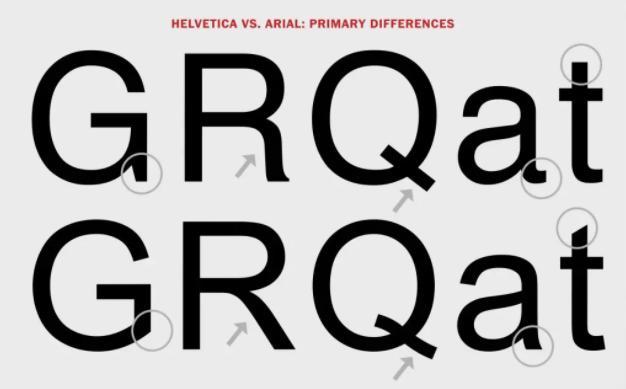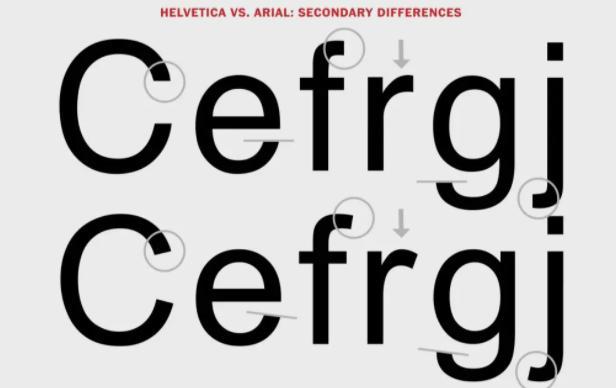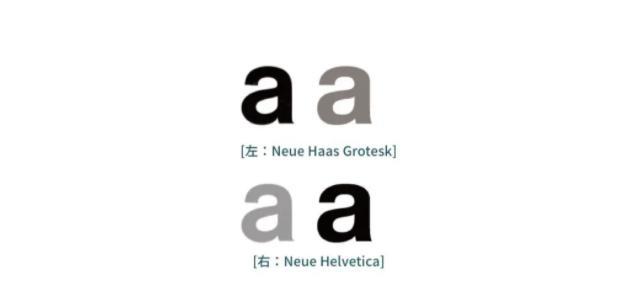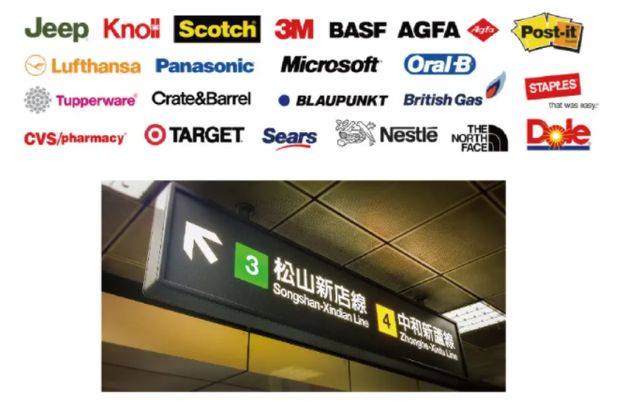
挽救铸字厂的事业的新字体
1950 年代,瑞士哈斯(Haas)铸字厂的老板爱德华奥夫曼(Eduard Hoffmann. 1892–1980)发现自己公司的无衬线体Franzsische Grotesk 和Normal-Grotesk 在市场上的占有率越来越低;相反地,对手伯特霍尔德(Berthold)铸字厂的Akzidenz-Grotesk 字体,却因搭上了国际主义设计风格(International Typographic Style)的顺风车,在当时显得更「现代」,也因此成为那个年代最受设计界欢迎的非衬线体。
但危机或许就是转机。哈斯铸字厂意识到他们需要设计一种新的字体──这个字体除了要更现代、简明、清晰之外,奥夫曼和字体设计师马克斯米丁格(Max Miedinger, 1910–1980)更想设计出一种真正「中性(neutral)」的字体,一种不带有其他涵义,让读者不会被字体本身的装饰分心、能够单纯传达文义的字体。
新字体的设计在 1956 年秋天如火如荼展开,米丁格在图纸上来回打稿。他先是统一了过去c, s, f, j 等字母笔画末端风格不一致的问题,空出了较大的x-height,让读者即使站在远处,也能清楚辨识;另外,他也缩小了字母与字母之间的间距,让整体文本看起来更为紧凑鲜明。
在新字體發表的前夕,米丁格將它命名為「Neue Haas Grotesk」,德文的語意為「新的/Haas 廠生產的/非襯線體」。1957 年,Neue Haas Grotesk 甫正式發表就獲得極大迴響,許多設計師好像終於找到了他們心目中的「理想字體」了。
不過對哈斯鑄字廠來說,這樣還遠遠不夠,要和其他鑄字廠的字體競爭,還需要藉由更廣泛、通用的媒介來宣傳 Neue Haas Grotesk。
以拉丁文命名
为了拓展新字体的使用率,1959 年奥夫曼和德国史丹普印刷厂 (D. Stempel AG )达成合作协议,让 Neue Haas Grotesk 成为该公司 Linotype 自动排字机的预设字体。
Linotype 在这里不是指 Linotype 公司,而是一种机器,是 Line-of-type 的缩写,意即「一行活字」。过去没有 Linotype 自动排字机时,排字员需要手动取下一个一个铅字,然后费时逐字排版。
报纸或杂志这类具时效性的印刷物,并不像书本有时间慢慢排,毕竟若今天的新闻要花好几天才能排完送印,届时岂不就成为了「旧闻」?
但在1884 年奥特玛·默根瑟勒(Ottmar Mergenthaler,1854–1899)发明Linotype 自动排字机后,将人工取字的过程大幅自动化,加速了由排版到送印出版间所需的时间,印刷厂可以在雇用和以往同样人数的排字员下,完成更多页面,造就了整个印刷产业的革新。
直到 1980 年代照相排版(phototypesetting)技术成熟前,世界上多数的报纸、杂志和海报都是透过这种机器进行排版。
达成协议固然是好事,不过史丹普的销售经理却觉得Neue Haas Grotesk 这个名字太饶口,建议重新命名为Helvetia(拉丁语瑞士(名词)之意),但因为这个名字已经被当时的保险公司和缝纫机公司采用了,所以奥夫曼建议使用另一个名字:Helvetica,这是拉丁文「瑞士的(形容词)」的意思。
顺带一提,身为一个拥有四种官方语言(德语、法语、义大利语、罗曼什语)的国家,并以中立为信念的瑞士政府,认为若采用其中一种语言来命名国家,可能会让使用另外三种语言的族群觉得不公平,所以最后决定用拉丁文Confderatio Helvetica(CH)作为正式的国名,毕竟拉丁语作为中世纪欧洲不同国家交流的媒介,似乎显得更「中立」。
1960 年,用在 Linotype 自动排字机上的 Neue Haas Grotesk 字型被重新命名为 Helvetica,但人工排字的铅字铸板仍以原来的名字销售。不过到了这个时候,其实可以把两者视为不同的字型了,因为Neue Haas Grotesk 已因被放到Linotype 自动排字机而对字型进行大幅度修改。于是 Helvetica 和 Neue Haas Grotesk 就此分道扬镳。
Helvetica:一个拥有 51 种字型的超大字体家族
早期的 Linotype 排字机对每个字母的字幅宽度限制是 18 个单位,这使得 Helvetica 必须在这个范围内重新绘制曲线。
随着Linotype 自动排字机的需求大增,哈斯和史丹普公司在仓促中做了不同字型大小的字体家族(font family)供各大印刷厂使用,像是更粗的、更细的、倾斜的Helvetica。也因为这个过程是急忙赶出来的,使得各种字型的比例都不太相同。
Linotype 的字模(matrix)是双工(duplex)运行的,可以想像成是同个印章上有标准体(regular)跟斜体(italic)、或是标准体跟粗体(bold),印刷时再依据需求,印出其中一种字体。这么做的优点,是字符模具的数量可以减半,但也因为要将标准体、斜体、粗体都镶在同个宽度的字模里,势必会让斜体字母之间看起来太宽,而粗体字母之间看起来又太窄。
为了让大写字母上方塞得进变音符号,每个字母的大小也必须重新压缩调整。随着时间过去,Helvetica 逐渐偏离 Neue Haas Grotesk 最初的设计。这些因为机器本身性能产生的限制,在迈入数位时代后仍被继承,成为现今我们看到的 Helvetica。
1983 年,Helvetica 被重制为新生的Neue Helvetica,除了修正过去因赶工,使各字型本身宽度和高度不同的问题外,也拓展了原有的字型,变成一个拥有51 种字型的超大字体家族;此外,为了让尺寸的扩充更容易,新版在比例上也做了些许妥协。而那个被遗忘在过去传统铅字时代的 Neue Haas Grotesk ,则在 2004 年被数位化,保留过去初版的精髓。
如今,Helvetica 被广泛运用于知名品牌的商标中,包含The North Face、Panasonic、3M、EPSON、HITACHI、LG、Microsoft、MOTOROLA、NBA、SUBWAY、SUZUKI、YONEX、WhatsApp 等,甚至在台北捷运的英文标示也能看到它的身影。